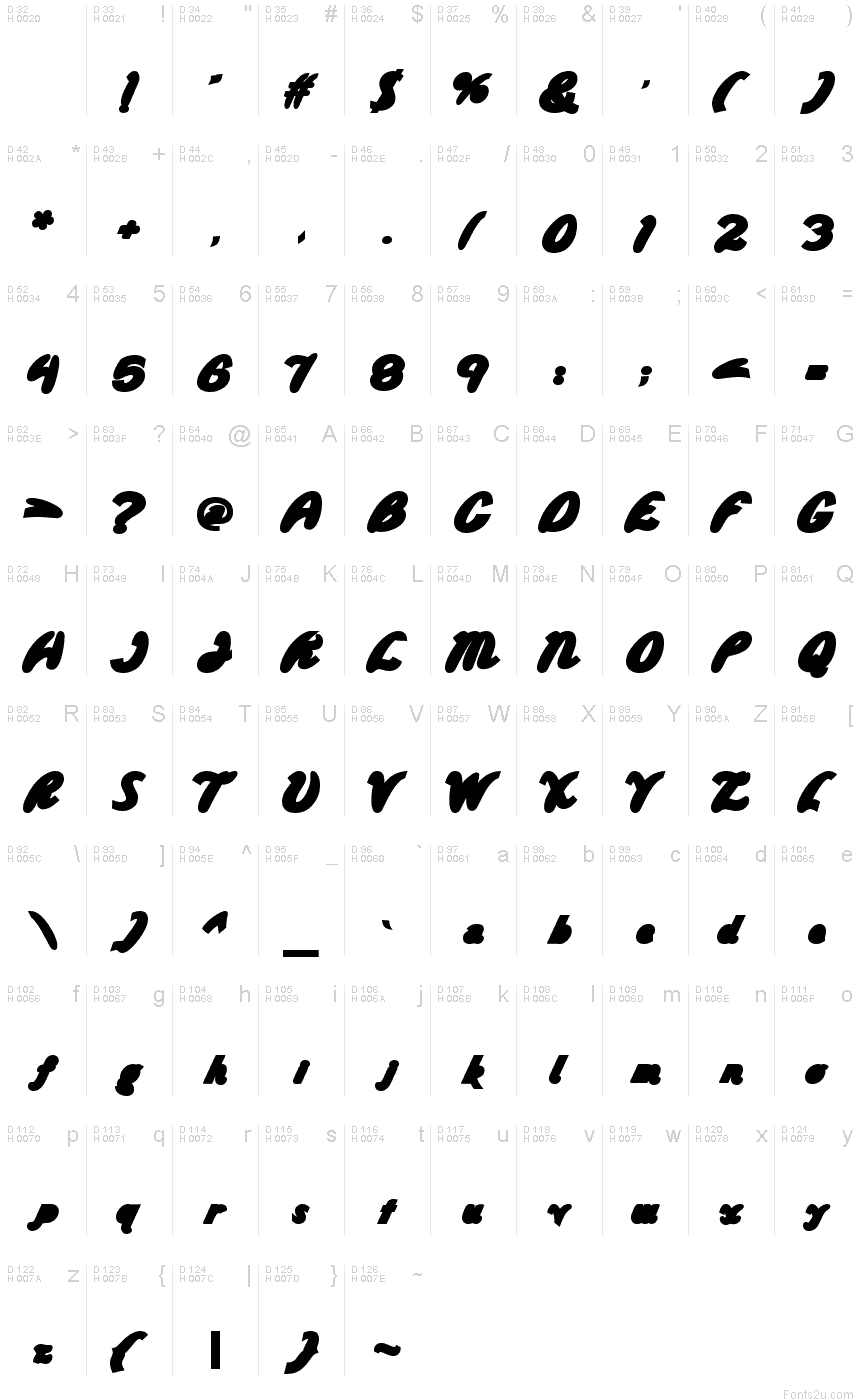
Wild Ride Back Fill
Wild Ride Back Fill autorstwa Michaela Hagemanna to darmowy, komiksowy krój displayowy z energią rodem z tuningu samochodów. Jego masywne, pędzlowane litery zderzają się ze sobą w szybkim pędzie. Formy są ciężkie, zaokrąglone i nieco niepokorne, z dużymi, zapętlonymi pociągnięciami i ostrymi wcięciami, które nadają krojowi klimatu hot-rodowych szyldów, zamiast typowej, grzecznej komiksowej kreski.
Świetnie sprawdzi się na nagłówkach plakatów, grafikach deskorolkowych, okładkach płyt, szyldach i ulotkach eventowych, gdzie napisy muszą być dynamiczne i sprawiać wrażenie „odręcznych”. Jako darmowy font idealnie nadaje się też do plansz tytułowych, szkiców logo i krótkich haseł, ponieważ połączone kształty tworzą jedną, wyrazistą formę, a nie tylko szereg pojedynczych liter.